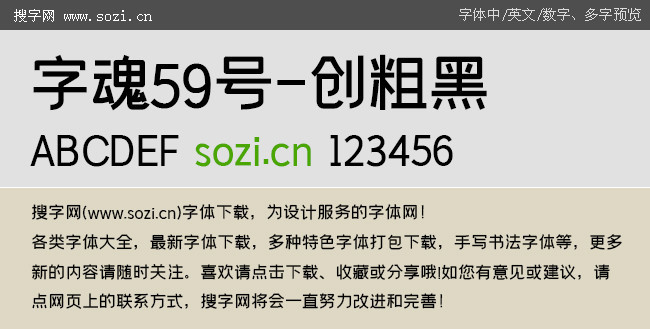
字魂59號-創(chuàng)粗黑
搜字網(wǎng)提供一款字魂59號-創(chuàng)粗黑中文字體下載,該字體是一款黑體字體,該字體包含6763個中文、字母、 符號和數(shù)字,具有現(xiàn)代、簡約、時尚 的風(fēng)格,可以滿足您設(shè)計上的各種需求,該字體主要用于廣告、新媒體、電商、媒體 等場景。